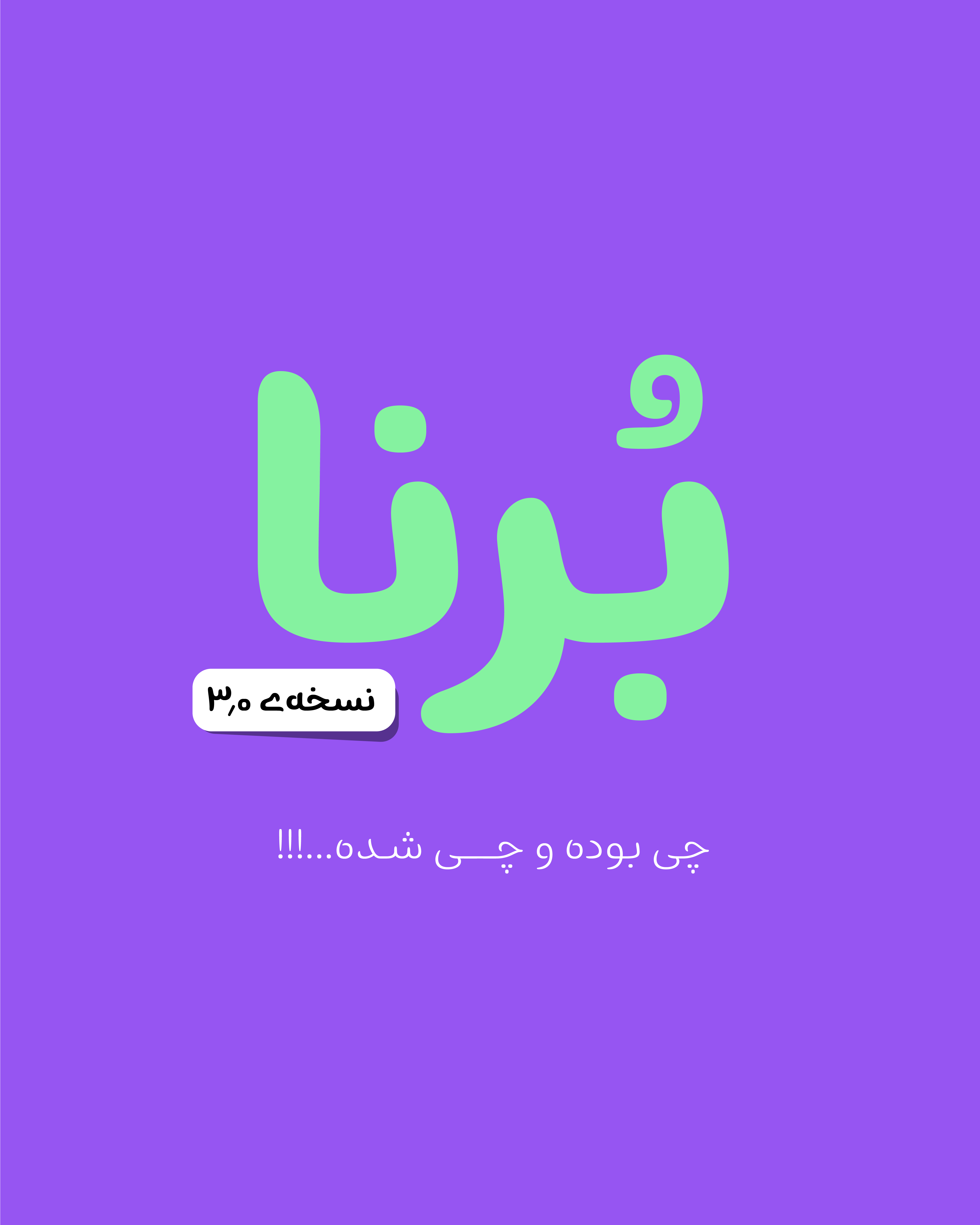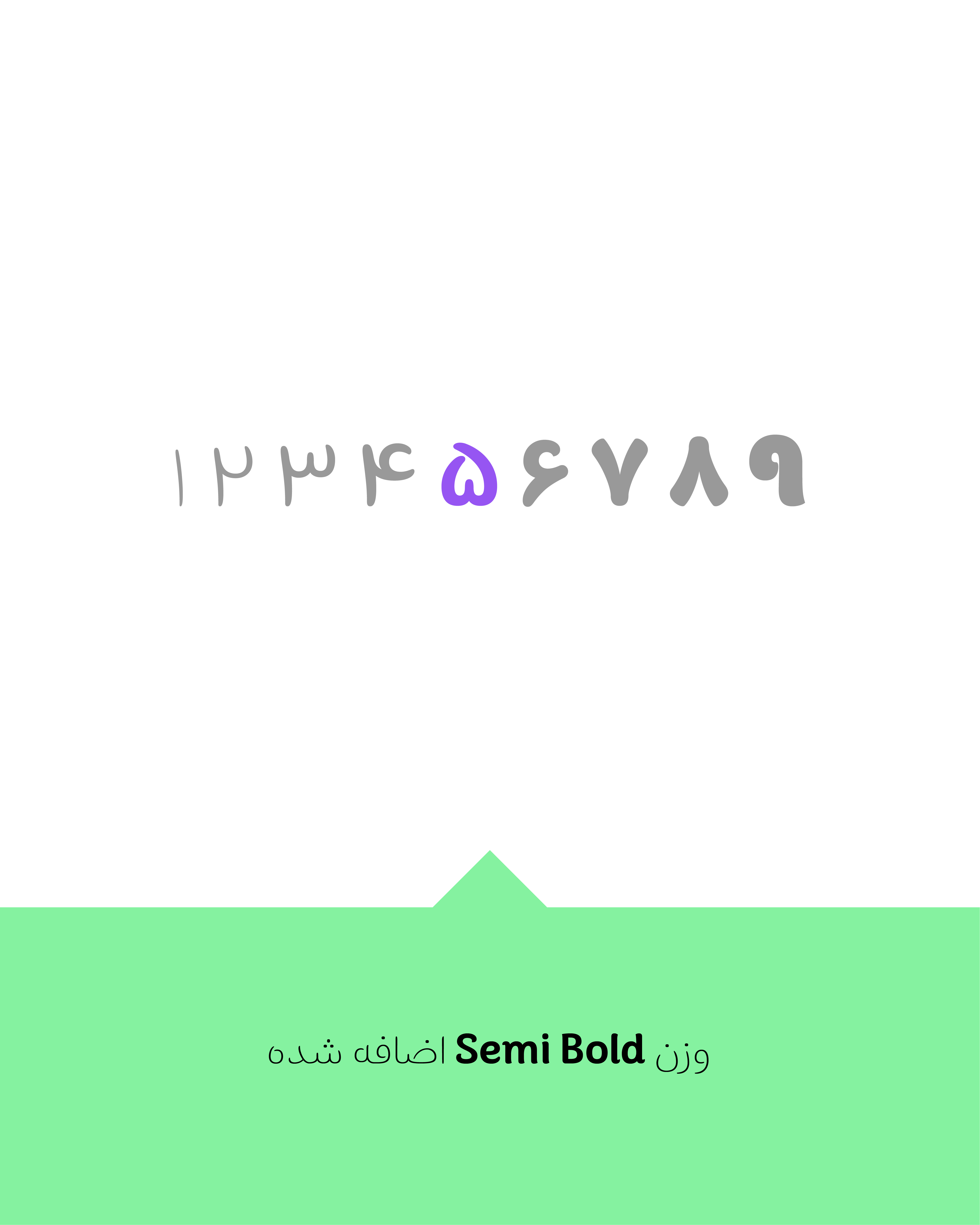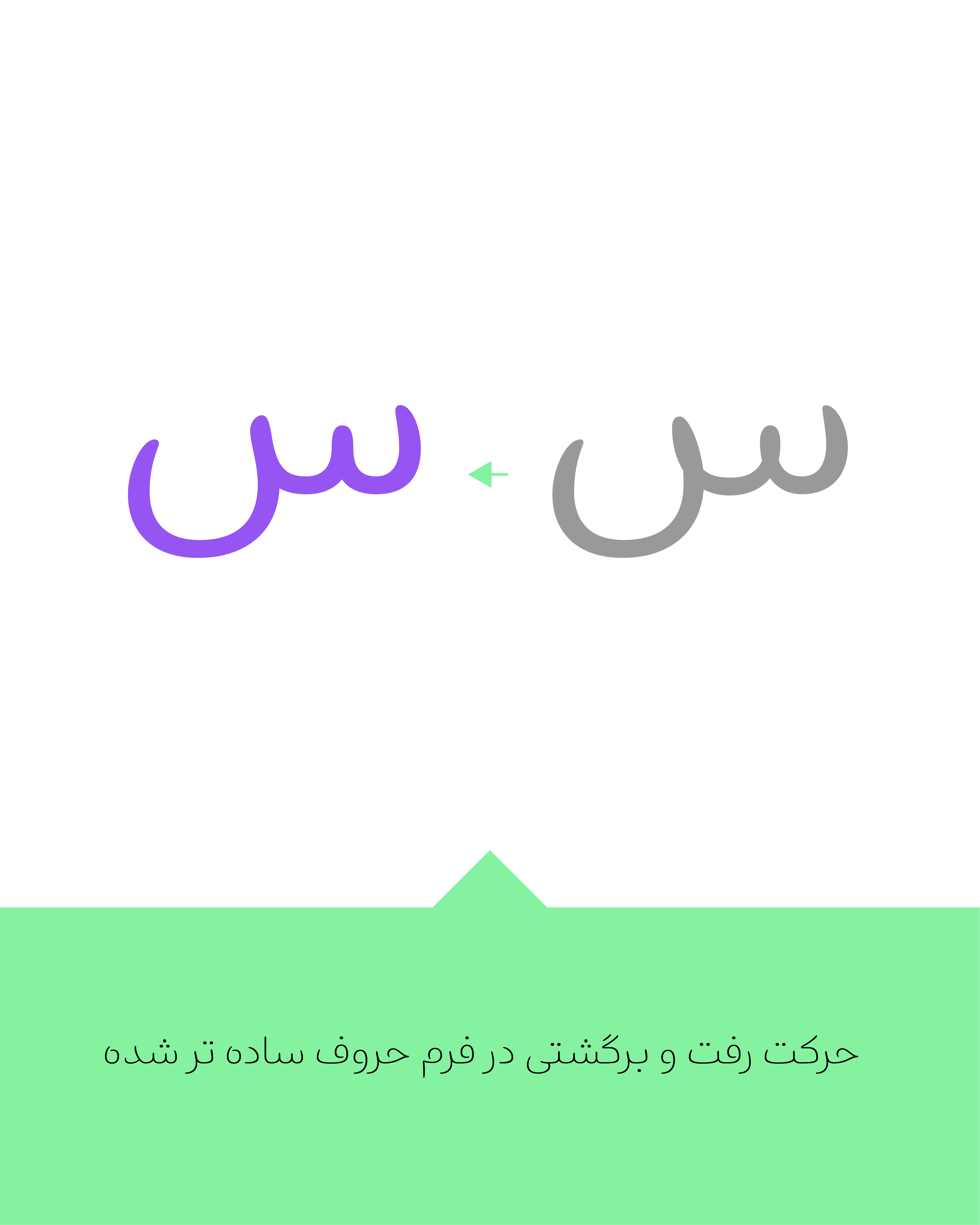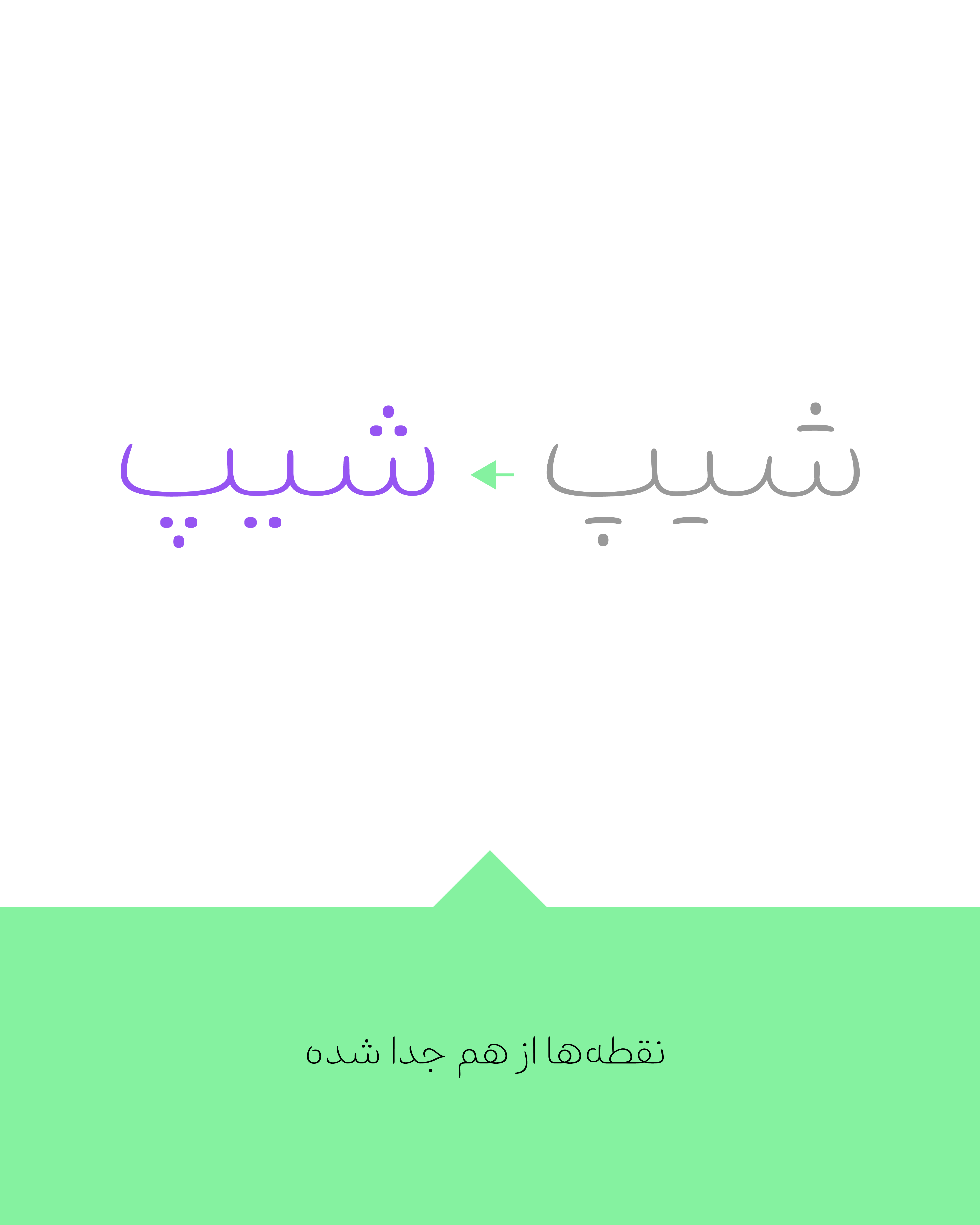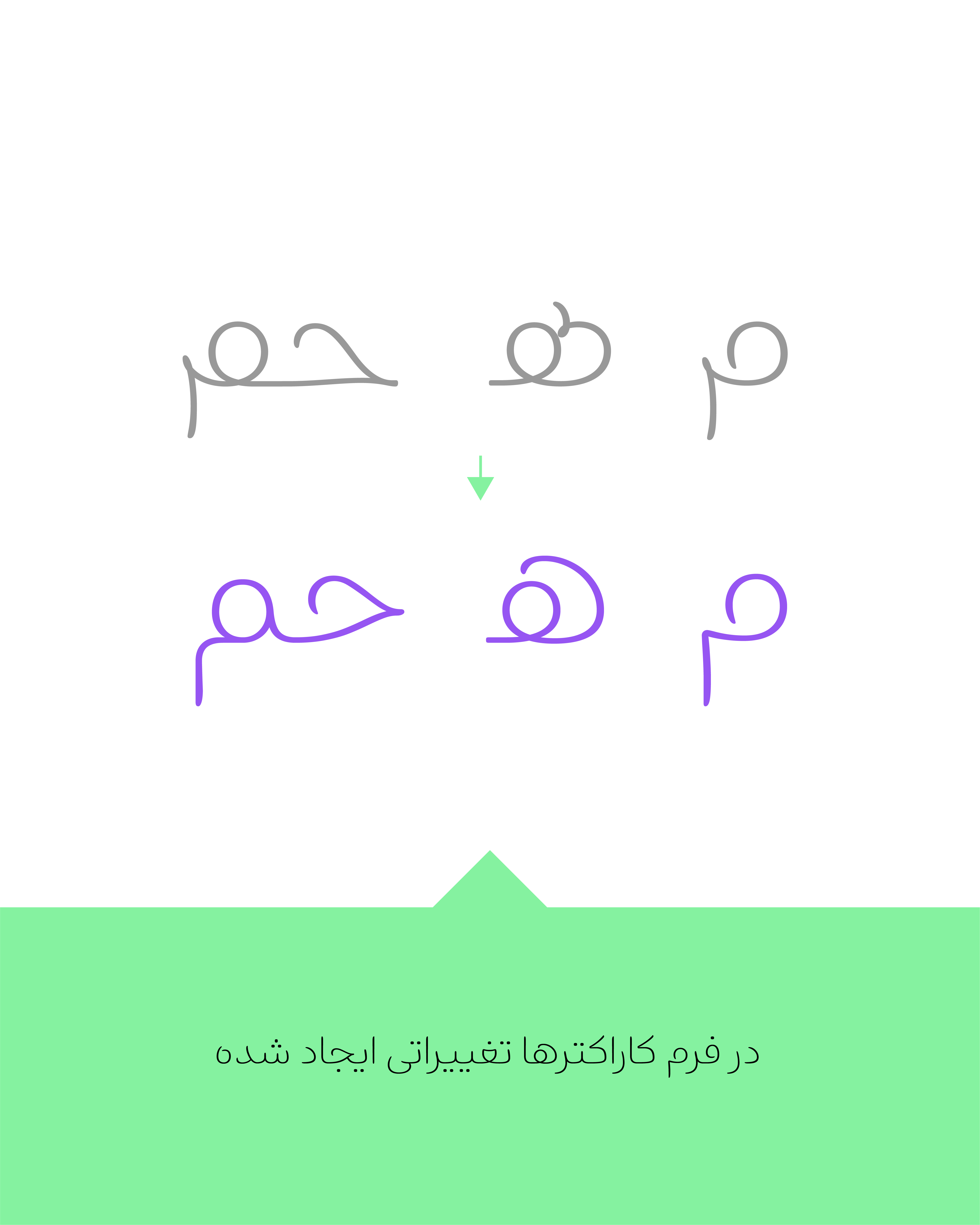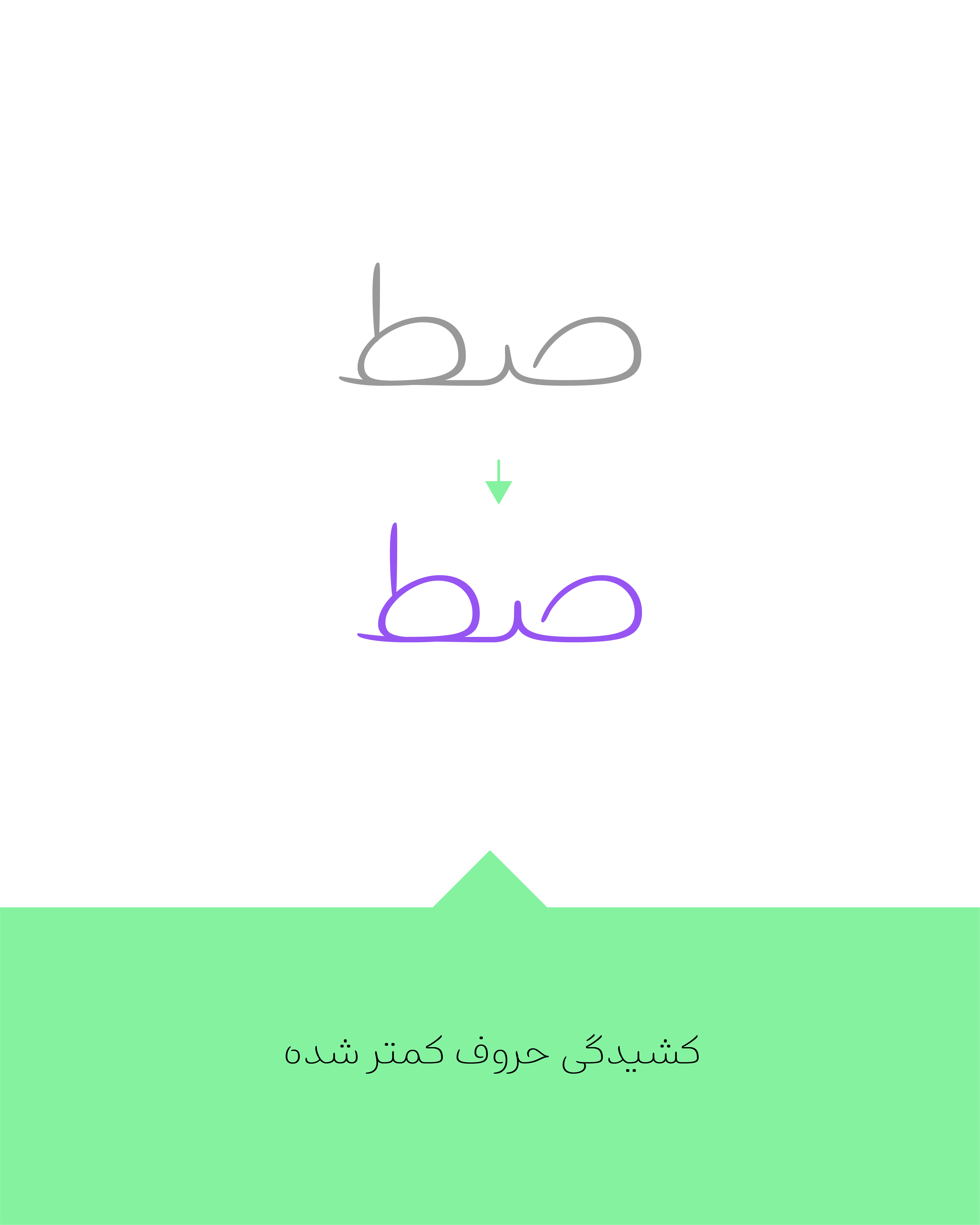
در نسخهی 3.0 فونت برنا چه تغییراتی میبینیم؟
- وزن Semi Bold اضافه شده
- حرکت رفت و برگشتی در فرم حروف سادهتر شده
- نقطهها از هم جدا شده
- در فرم کاراکترها تغییراتی ایجاد شده
- کشیدگی حروف کمتر شده